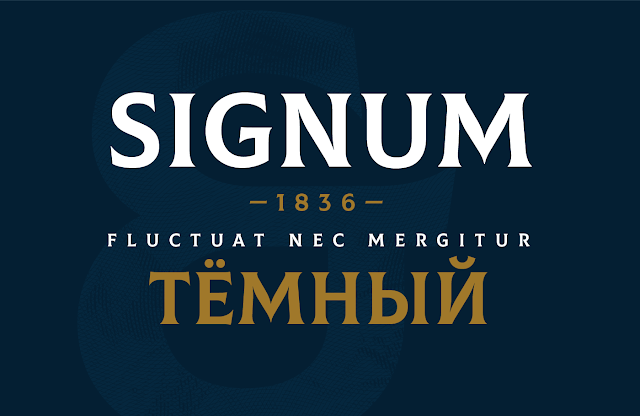
Hoy os traemos una joya de tipografía gratuita con una calidad exquisita como no podría ser de otra forma si tras su diseño están los chicos de Fontfabric.
Os hablamos de Colus, una familia tipografica display inspirada en las letras clásicas talladas en la piedra de la antigua Roma.
Con esta tipografía que podemos descargar totalmente gratis conseguiremos diseñar titulares impactantes, logotipos, o casi cualquier aplicación puesto que soporta muchos idiomas latinos y cirílicos, además de ligaduras y otros caracteres alternativos muy interesantes.
Una joya de tipografía gratuita.